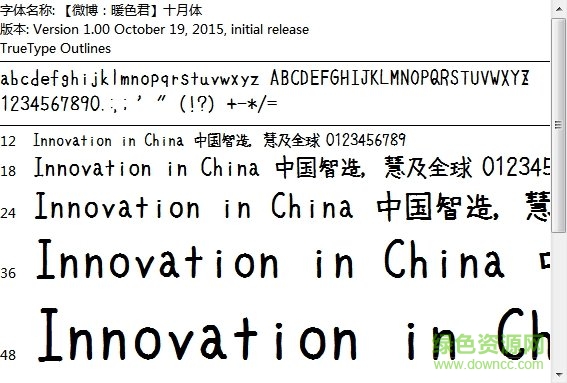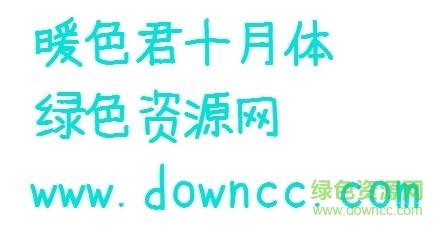
暖色君十月體
十月體微博暖色君修改的一款手寫字體,支持日語、韓語、中文黑體簡繁等多種語言,滿足大家日常生活的多種要求,快來綠色資源網(wǎng)試試吧!
新浪微博暖色君十月體特點
十月字體有著極其精簡的外觀,和十分活動的兒童字體造型,給你質(zhì)樸可愛的視覺感受,字庫完整,讓用戶使用起來更加隨性,讓你的平面設(shè)計、包裝設(shè)計更加出彩!
暖色君字體系列都有著十分悅目的外觀,以手寫體為主,充滿了生動嬌憨的可愛風(fēng)格,讓人閱讀起來更加清晰醒目。